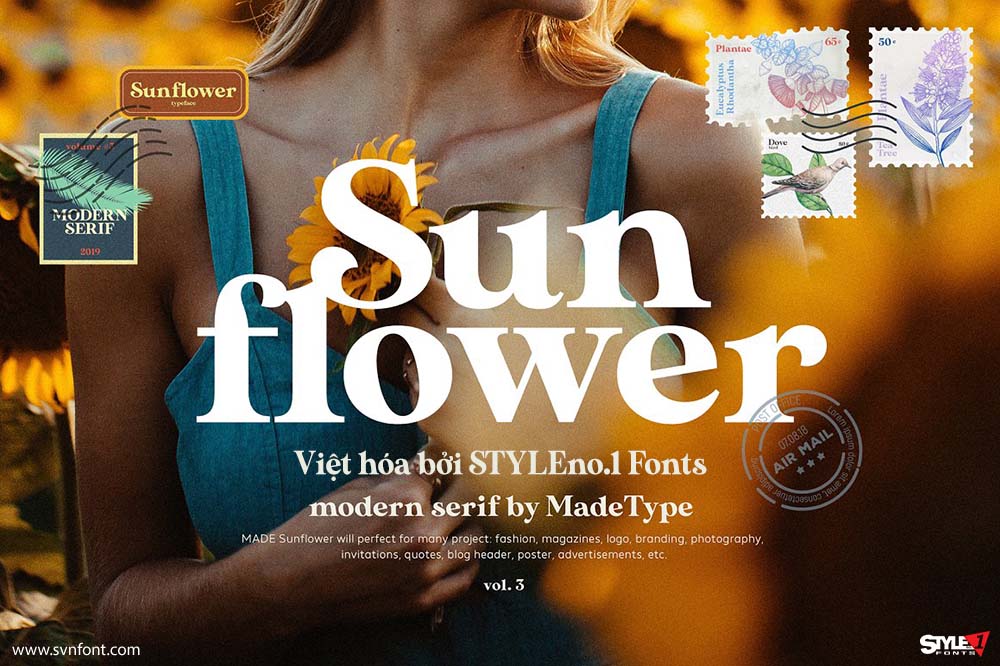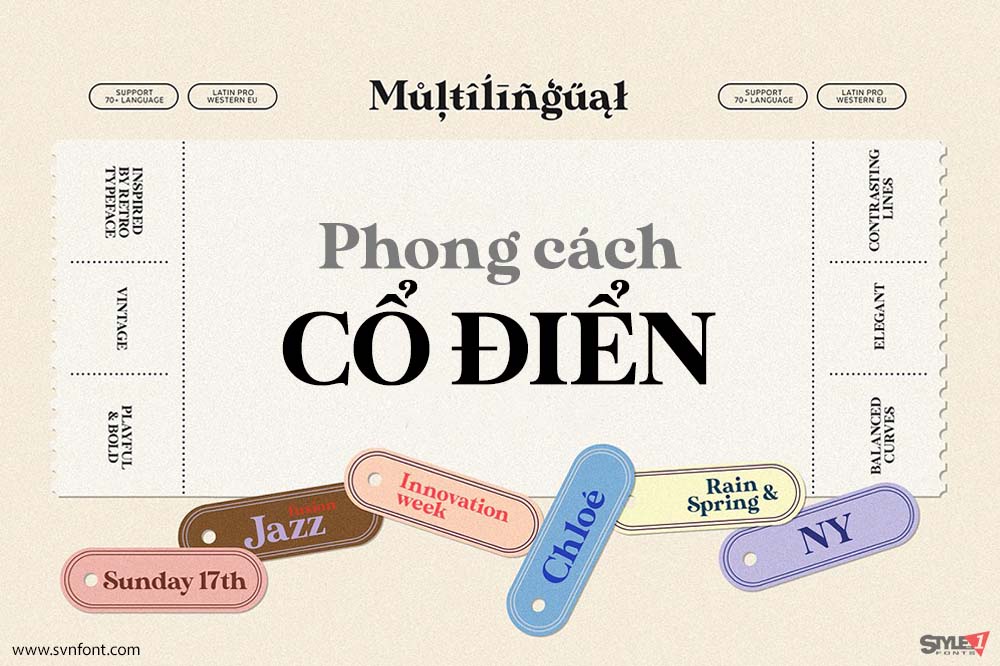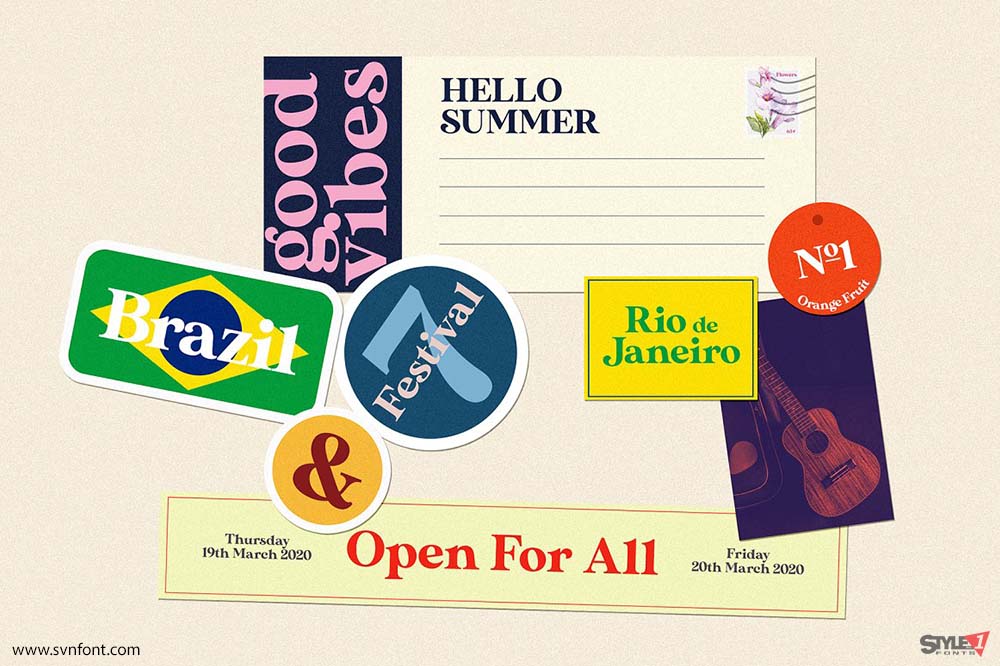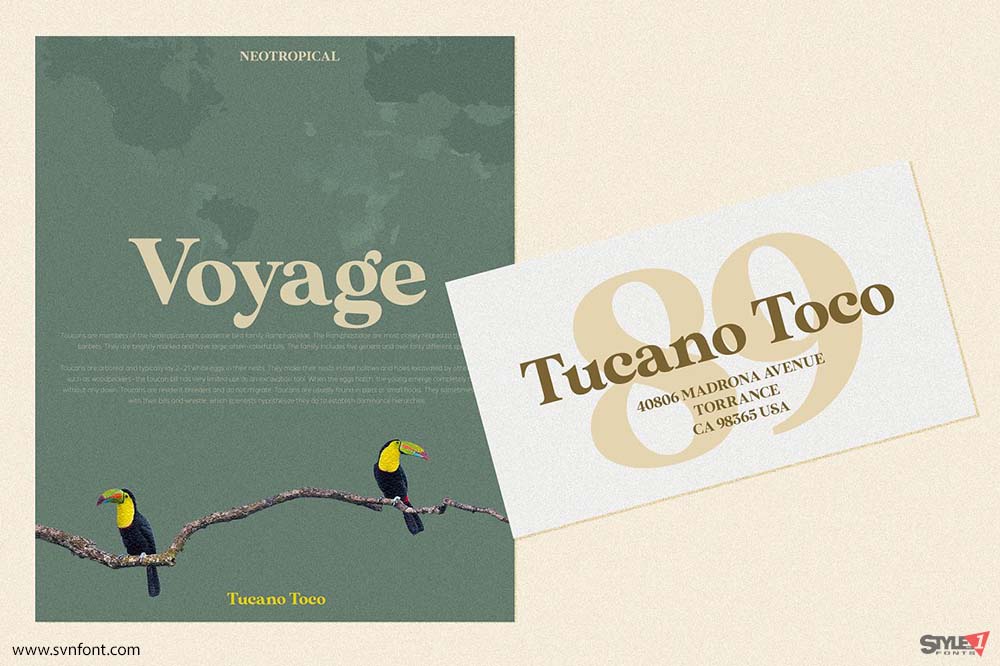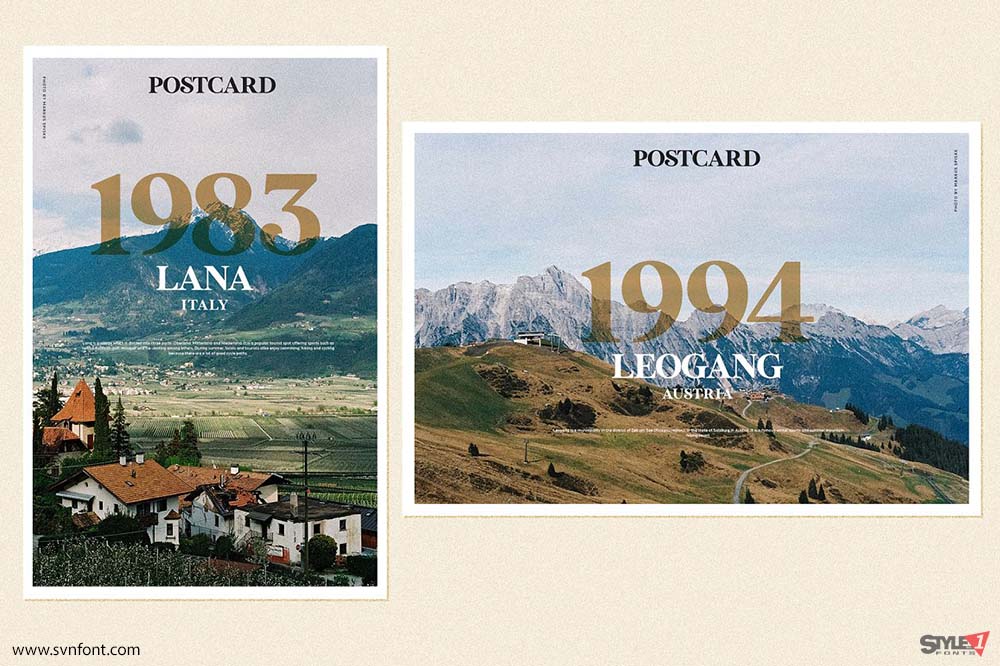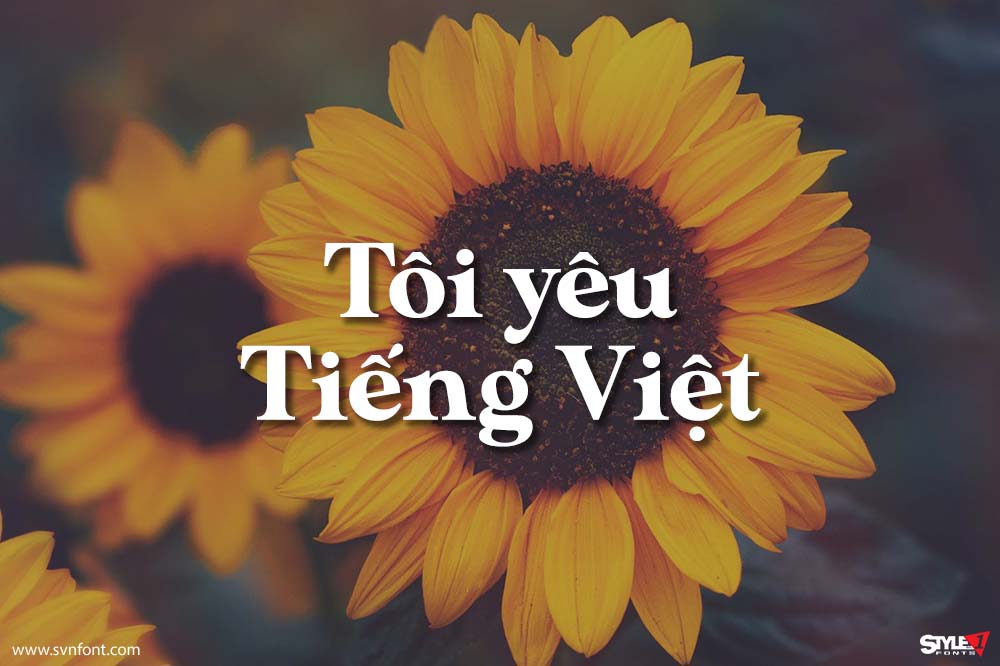
Font Việt Hóa SVN - Sunflower Mang Phong Cách Cổ Điển
Janelotus - một font serif hiện đại nhưng chứa nhiều yếu tố cổ điển. Font hoàn hảo cho nhiều dự án: thời trang, tạp chí, logo, thương hiệu, nhiếp ảnh, trích dẫn, tiêu đề...
Nhà thiết kế: MadeType
Nhà phát hành: MadeType
Việt hóa: STYLEno.1 Fonts